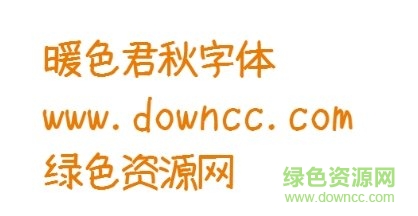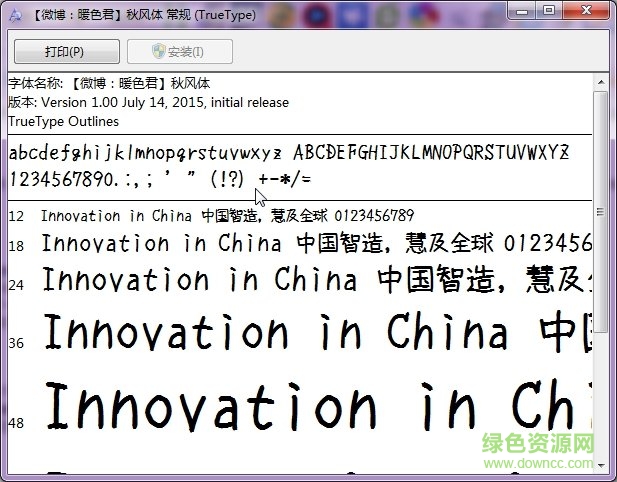
暖色君秋字體ttf是新浪微博字體達人暖色君分享的一款秋風體字體,支持繁簡體輸入,自己秀氣柔美,給人秋季安靜恬適的獨特體驗,流暢的結(jié)構(gòu)和筆觸給你清晰的視覺閱讀感受,來綠色資源網(wǎng)免費下載吧!
秋風體,由微博暖色君分享,字體結(jié)構(gòu)分明,無論中文還是英文都有自己的書寫特色,較常規(guī)字體更黑一些,讓視覺呈現(xiàn)更加顯眼,結(jié)合了手寫字體和書法字體的風格,可以廣泛運用于藝術(shù)設(shè)計、海報設(shè)計、名片設(shè)計等諸多場合。